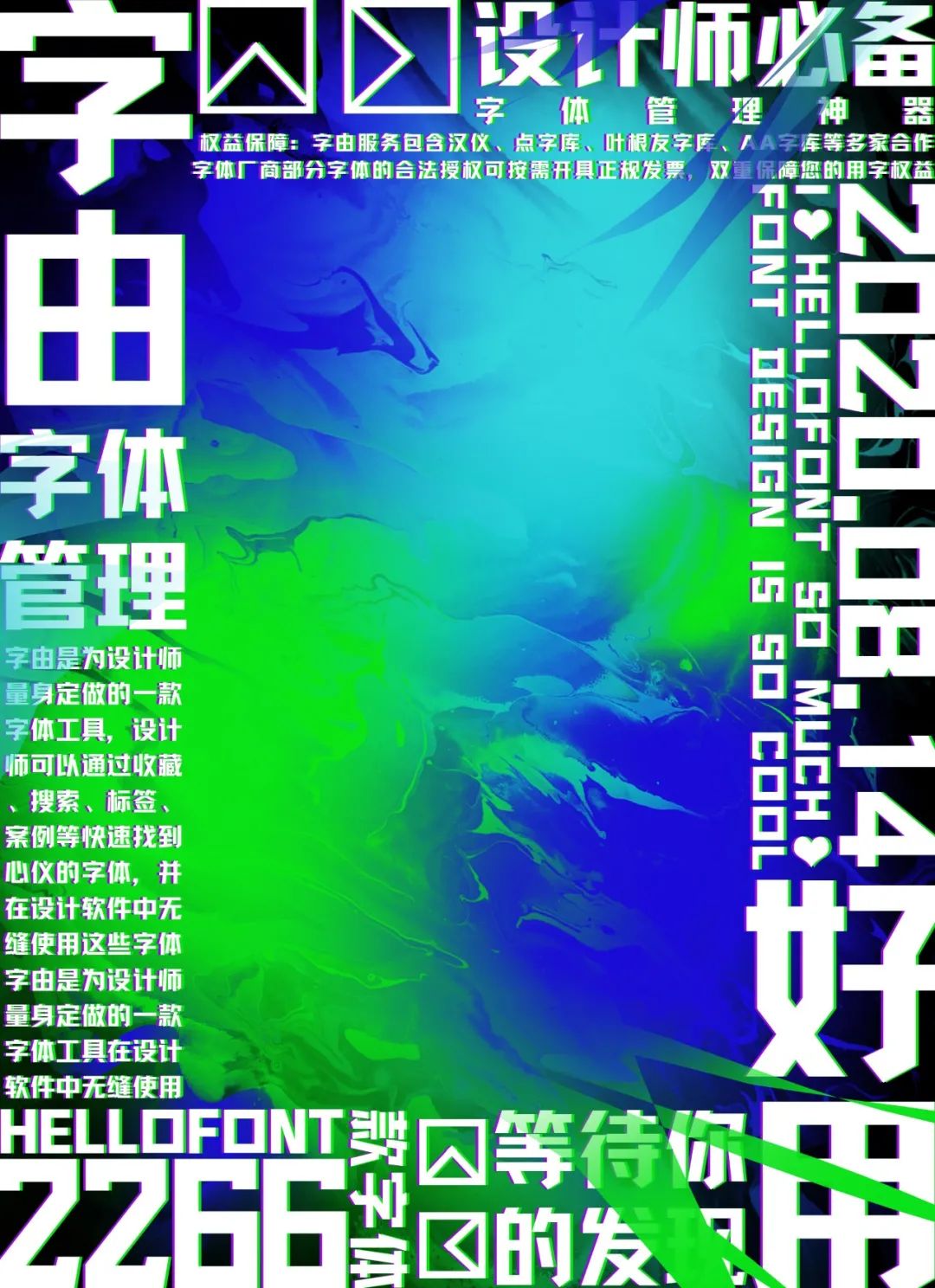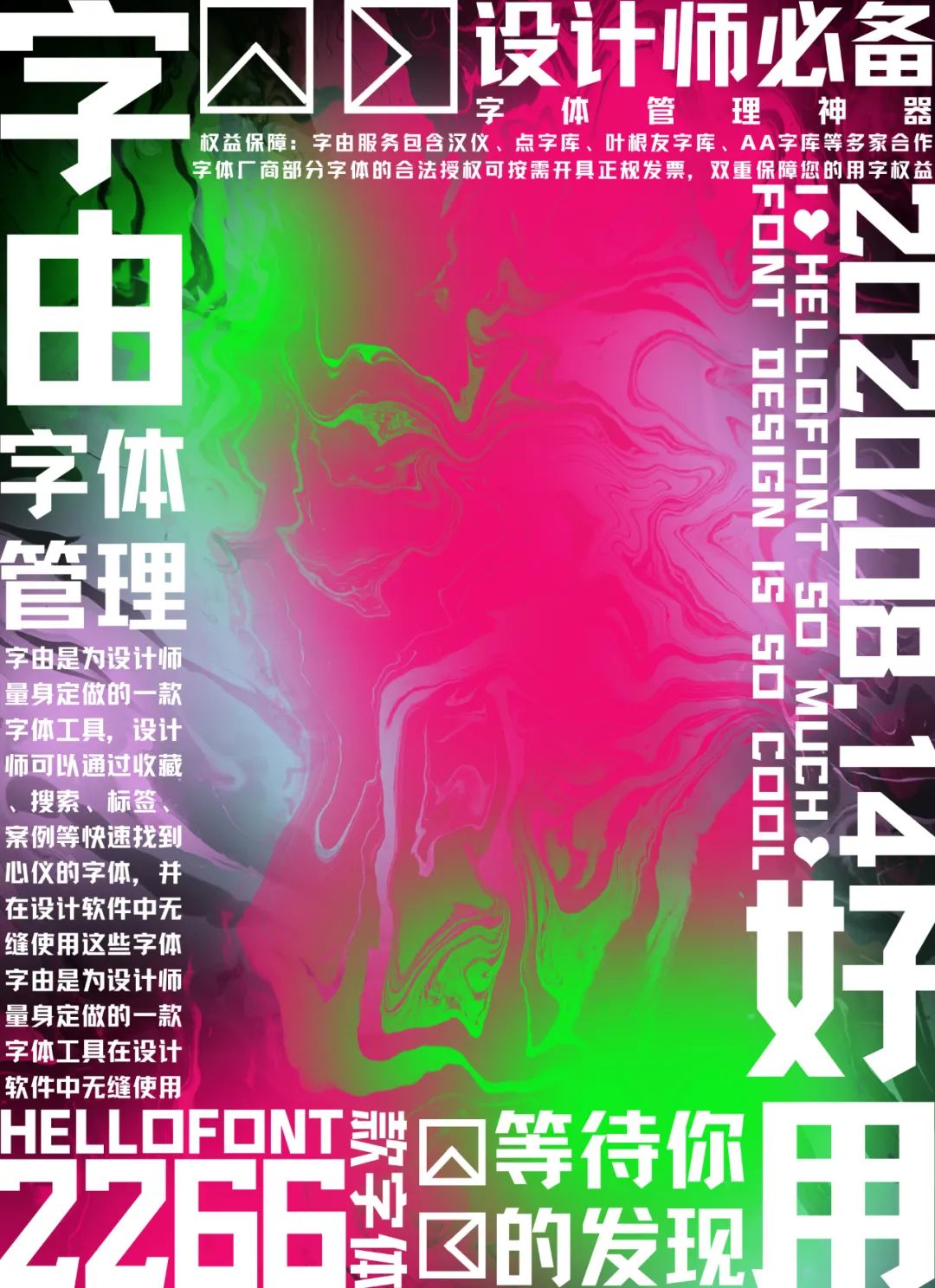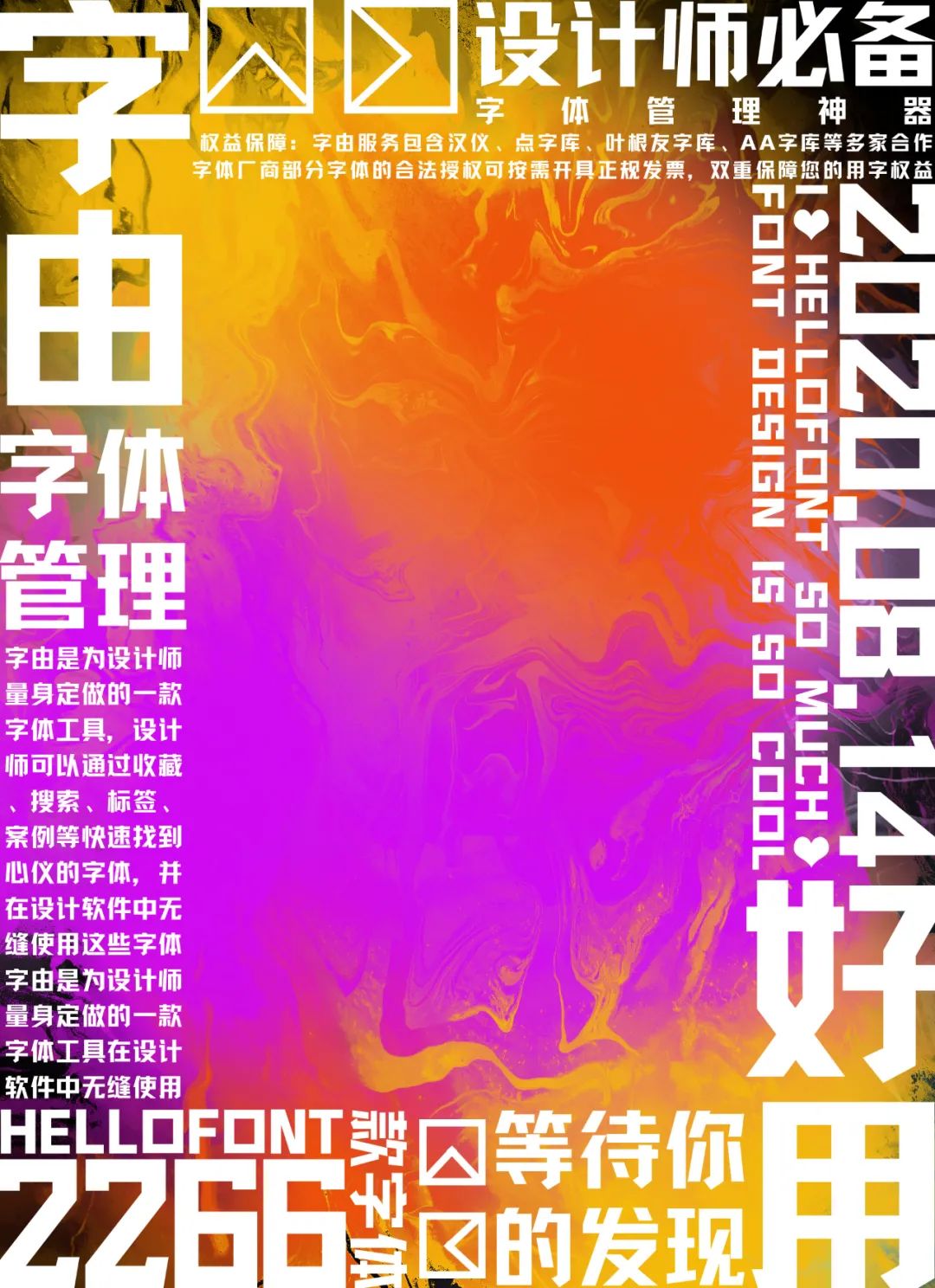
没背景素材?也能用PS轻松做迷幻海报~
近些年迷幻风格的海报非常受欢迎,传递给人一种神秘感和潮流感。
首先打开PS,为文字内容做一个简单的排版,这里用到的字体是点字倔强黑,一款经典好用,在海报中出镜率很高的黑体字~
在免费商用图片网站上找一些素材图片,给大家看看柚子找的~
将这些图在PS里打开另存为PSD格式备用。
回到我们的文字排版,新建一个图层,用柔边画笔选择喜欢的颜色,在画布上随意挥洒。
选择菜单栏滤镜-扭曲-置换,为了效果更明显,将两项参数都调为100。
点击确定后,选择我们刚才另存为PSD格式的素材文件。
用同样的方法,多叠几个素材文件,并将背景色设置为黑色,文字设置为白色,得到下图效果。
用同样的方法换个颜色试试~
哈哈😸~是不是很好玩~下面我们给刚做好的海报加一点细节:用选取工具在你觉得空的位置上随意框选一下,填充上颜色。
再用柔边橡皮擦擦一下边缘,产生虚实对比的变化。
用同样的方法添加合适数量的裂纹。
将文字排版图层复制两层,根据整体画面上色,这里柚子把一层填充为绿色,一层填充为紫色,并把他们调整到白色字体图层的下方,形成两个阴影。
看看成品效果吧~🎉